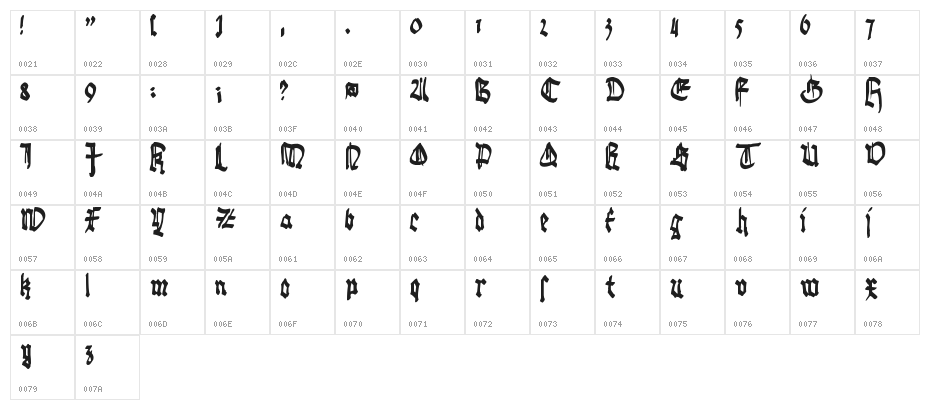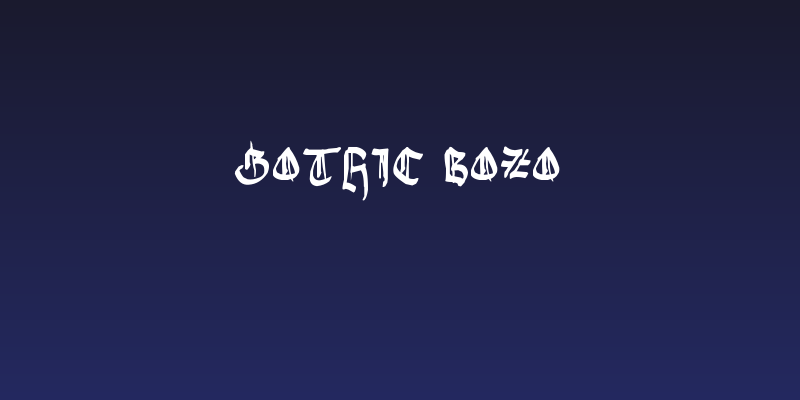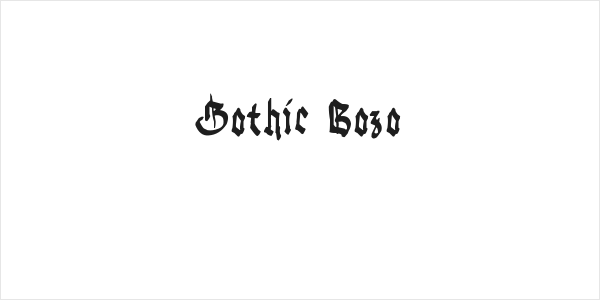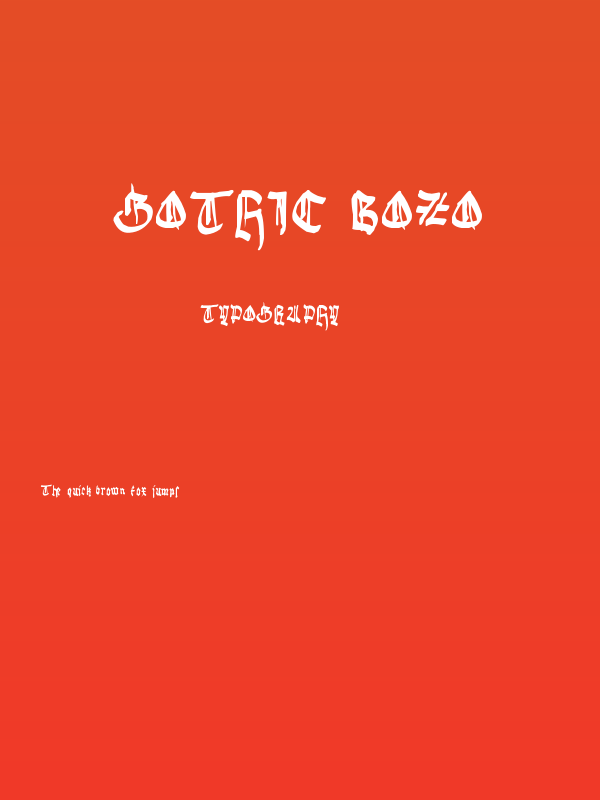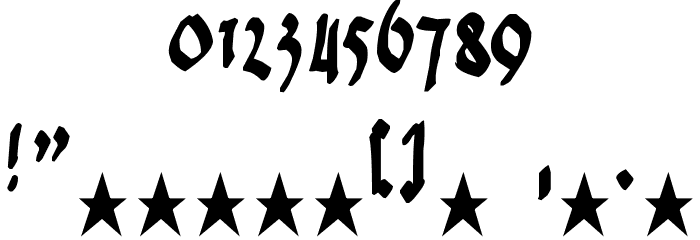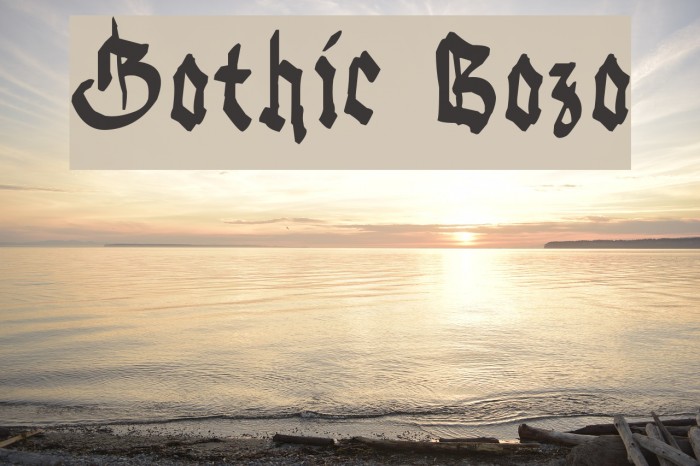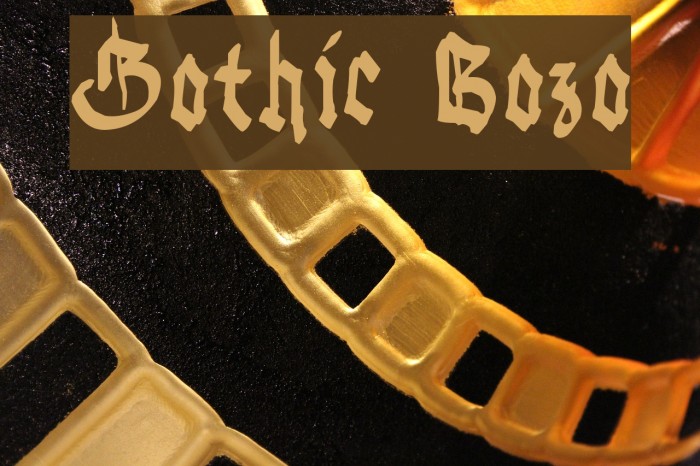
Gothic Bozo Font
Fonts by SDFonts - Ritzy
| Estilo general | Vintage |
| Caso de uso | Logos, Headlines, Decorative text |
| Proyectos propuestos | Ideal for historical-themed designs, book covers, posters, and branding that requires a medieval or dramatic flair. |